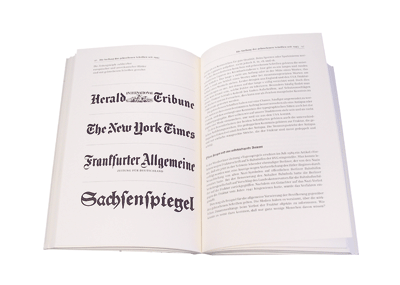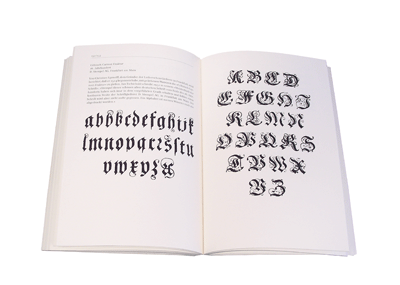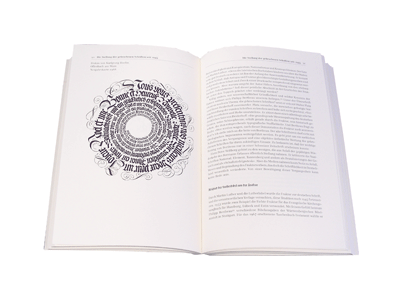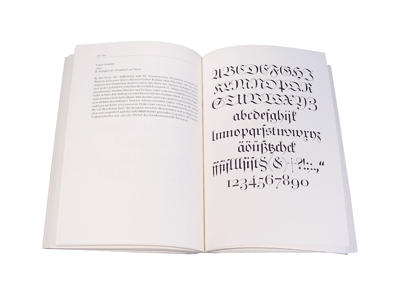
Ein undogmatisches Plädoyer für die Schönheit der gebrochenen Schriften.
Der Antiqua-Fraktur-Streit wurde lange Zeit erbittert und ideologisch geführt. Doch auch nachdem der Streit endgültig entschieden war und die Antiqua die allgemeine Verkehrsschrift für das Deutsche geworden ist, hören die Debatten nicht auf. Die Freunde der gebrochenen Schriften verteidigen diese nach wie vor mit ideologisch geprägten und sachlich und historisch kaum tragfähigen Argumenten. Das Buch Albert Kaprs bietet dazu einen erfreulich sachlichen Gegenpol. Kapr gelingt es, die Geschichte der gebrochenen Schriften zu erzählen, ohne sich auf eine Seite der damals zerstrittenen Lager zu schlagen.
Das Buch gliedert sich dabei in folgende Bereiche:
Gut die Hälfte des Buches machen die historischen Abhandlungen aus. Dies reicht von der Entstehung der gebrochenen Schriften und der Ausbildung ihrer verschiedenen Gattungen bis hin zur Dokumentation des Antiqua-Fraktur-Streites, der schon Ende des 18. Jahrhunderts begann und in der ersten Hälfte des 20. Jahrhunderts kulminierte. Auch die unterschiedliche Entwicklung beim Einsatz der gebrochenen Schriften in Ost- und Westdeutschland nach dem 2. Weltkrieg wird besprochen.
Im zweiten Tel des Buches übernimmt zunächst Hans Peter Willberg mit einem Aufsatz über das »falsche Image der Fraktur«.Anschließend zeigt Kapr auf circa 100 Seiten die seiner Meinung nach schönsten gebrochenen Druckschriften auf und erklärt diese jeweils kurz.
Den Abschluss bilden ein Aufsatz von Friedrich Forssman über die klassischen Satzregeln gebrochener Schriften und eine Zusammenstellung Willbergs von Anwendungsbeispielen aus dem Buchdruck.
Untertitel: Form und Geschichte der gebrochenen Schriften